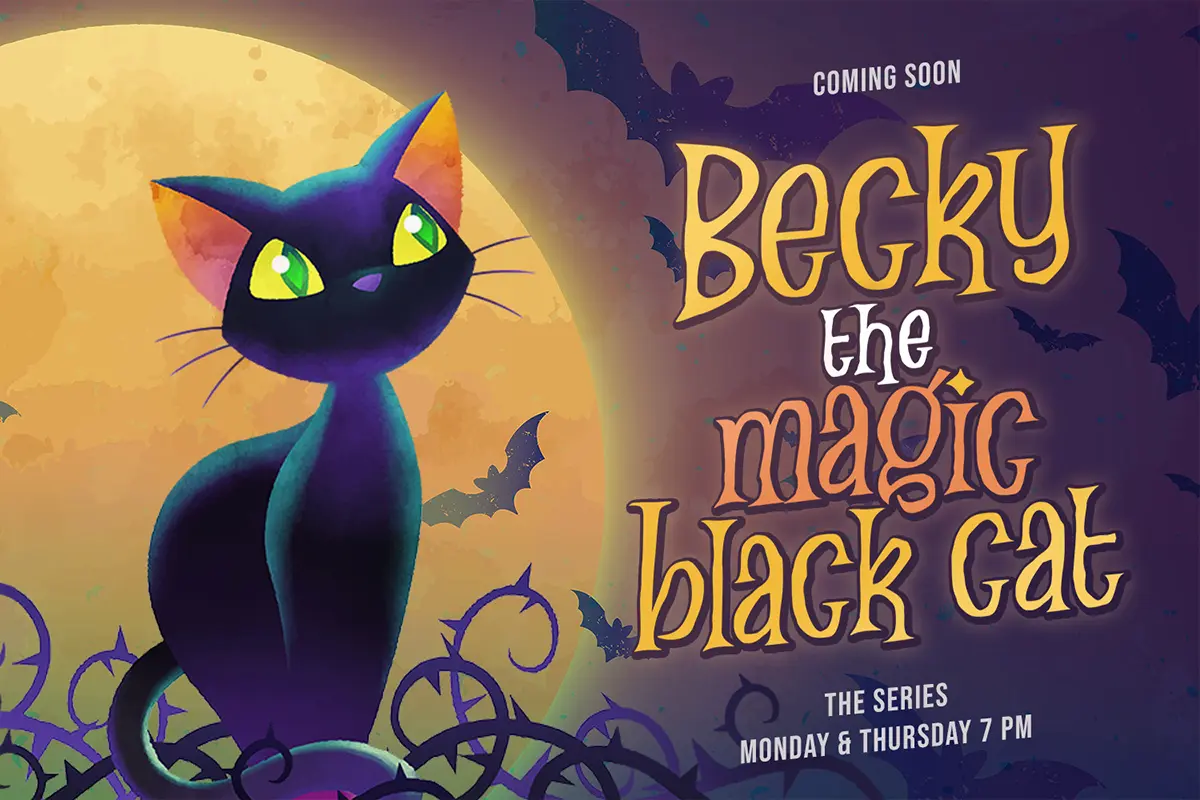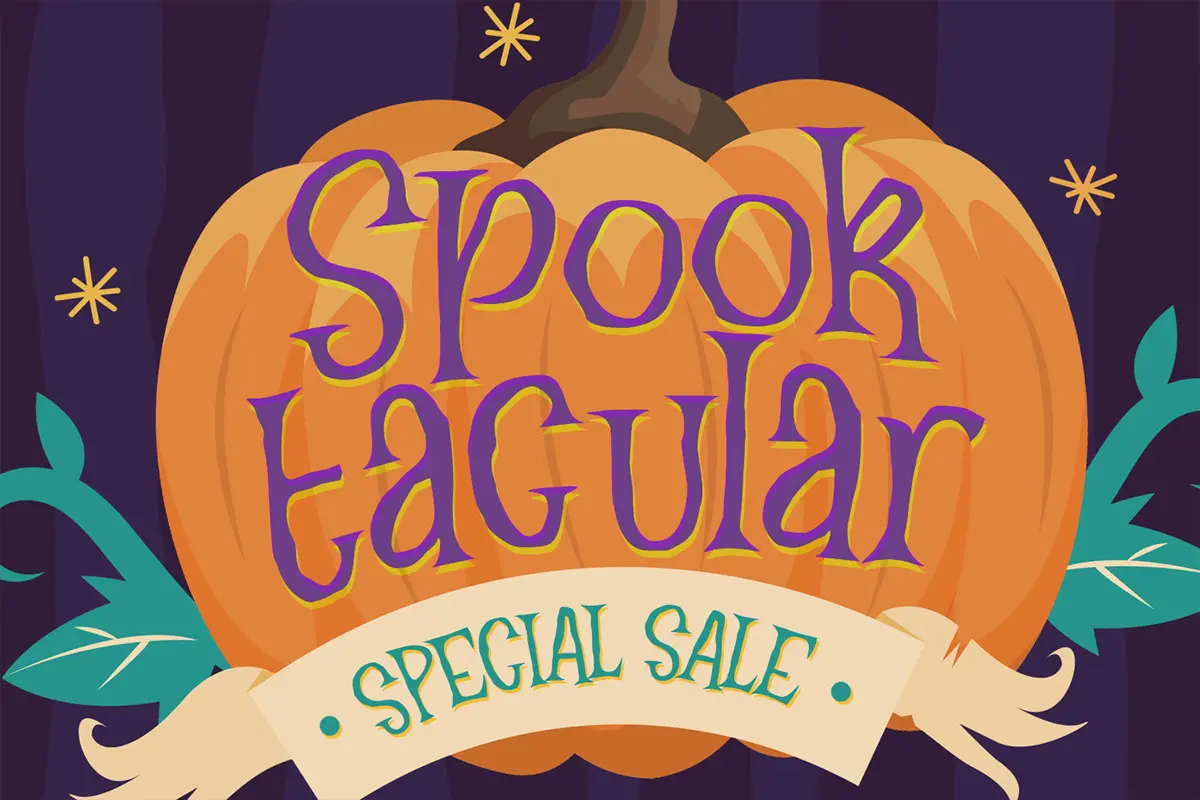
فونت Mr Halloween یک فونت نمایشی فانتزی و ترسناک با طراحی خاص هالووینی است که برای طراحی پوستر، تراکت، لوگو، تایپوگرافی، بنرهای تبلیغاتی و پروژههای گرافیکی مناسبتی کاربرد دارد.
Mr Halloween یک فونت انگلیسی نمایشی (Display Font) با طراحی خلاقانه و حالوهوای ترسناک هالووین است که میتواند جلوهای متفاوت و جذاب به پروژههای گرافیکی شما ببخشد. سبک خاص حروف در این فونت باعث میشود نوشتهها ظاهری مرموز، فانتزی و حرفهای پیدا کنند و برای طراحیهای مرتبط با هالووین انتخابی ایدهآل باشد.
این فونت برای طراحی پوسترهای هالووین، تراکتهای تبلیغاتی، لوگو، کاور شبکههای اجتماعی، بنرهای مناسبتی، دعوتنامه جشنها و انواع پروژههای چاپی و دیجیتال کاربرد دارد. ترکیب ظاهر فانتزی و خوانایی مناسب باعث شده تا Mr Halloween هم برای عناوین بزرگ و هم برای طراحیهای خلاقانه مورد استفاده قرار گیرد.
اگر به دنبال یک فونت هالووینی خاص و متفاوت برای پروژههای مناسبتی خود هستید، Mr Halloween میتواند انتخابی جذاب و حرفهای باشد.
ویژگیهای فونت:
- طراحی فانتزی و ترسناک
- مناسب پروژههای هالووین
- فونت نمایشی (Display Font)
- مناسب عناوین و تایپوگرافی
- طراحی خلاقانه و حرفهای